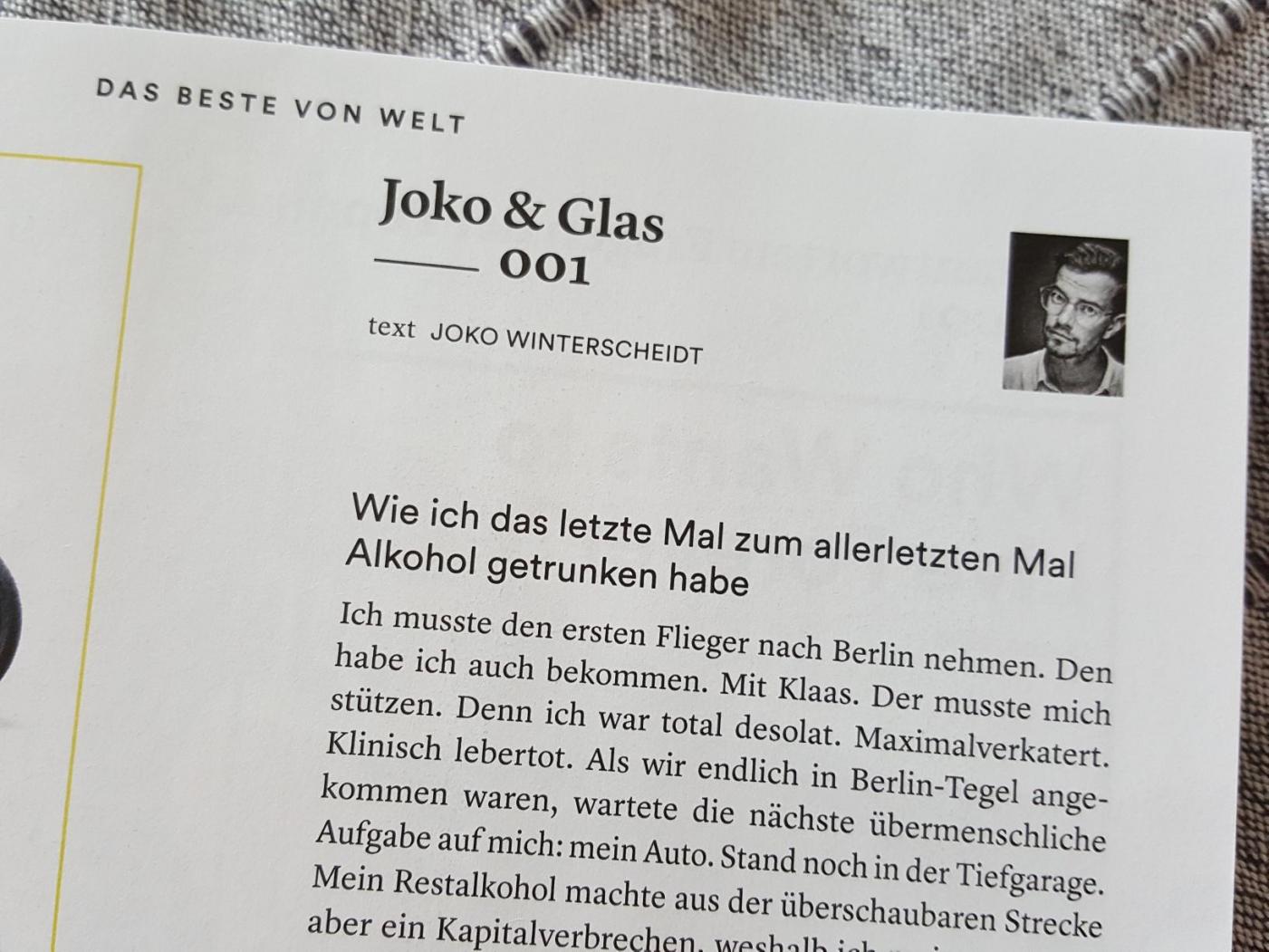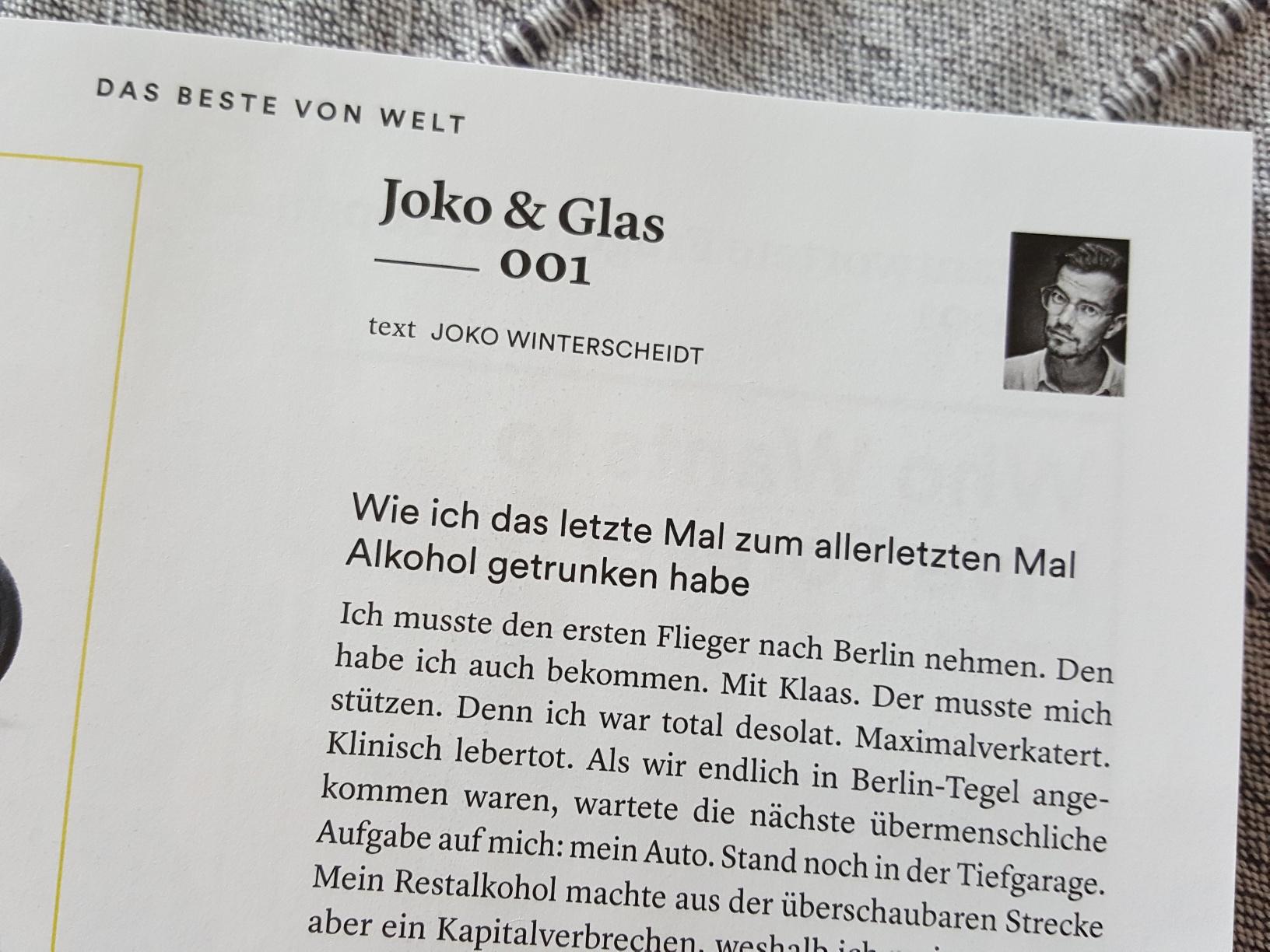
Schriften von JWD-Magazin
suche die im neuen Magazin von Joko Winterscheid genutzten Schriften für Text ("Brotschrift") und Überschriften. Habe bis jetzt nur gefunden, dass das Layout Heico Forster verantwortet. Würde mich freuen, wenn mir jemand helfen könnte :-)
Gelöst von D2C
Die Überschriften (Sans-Serif) sind in der LL Circular von Laurenz Brunner gesetzt, erschienen bei Lineto.
Fließtext habe ich bereits selbst herausgefunden: die Lyon von Kai Bernau, erschienen bei Commercial Type.
Ja, finde ich auch. Habe für ein Projekt damals die Guardian gekauft, aber werde auf die Lyon ganz sicher auch ein Auge werfen. Die Circular hat einen stolzen Preis, da muss ich noch überlegen :-))
Vielen Dank für den Hinweis, Superseite! Die Real hab ich sogar schon, dass die der 1. Vorschlag ist, hätte ich jetzt nicht gedacht.. Die Neuzeit Grotesk hatte ich zunächst in Verdacht, die Schrift zu sein, sie läuft nur etwas schmaler, aber die Ziffern 0-9 sind denen der Circular sehr ähnlich. Checke die anderen aber auch mal durch . Die Seite https://www.typewolf.com/site-of-the-day/fonts/lyon-text gibt noch andere Non-Serifen als Kombi an, aber die, die mir gefallen, sind noch teurer als die Circular :-)
Wenn es um Alternativen geht: die Neurial ist vielleicht eine Überlegung wert (Deni Anggara für Indian Type Foundry, 2018). Sie hat zumindest auch das im Moment so angesagte /t mit dem Radius in der Stamm-Querstrich-Ecke (war die Circular eigentlich die erste Schrift mit diesem Merkmal?). Die Schriften von Indian Type Foundry sind außerdem in der Regel recht gut gehintet, falls das für dich eine Rolle spielt. Die Circular dagegen bröckelte stellenweise auf weniger hochauflösenden Displays, als ich mal mit ihr fürs Web gearbeitet habe. Dafür hat die Neurial keine »echte« Kursive, nur Oblique-Schnitte.
Dann gibt es noch die Neuzeit Office als Alternative (Akira Kobayashi für Linotype, 2006) – ähnlich der auch von Identifont vorgeschlagenen Neuzeit S, aber etwas luftiger als diese. Sie hat mal in einem Projekt von mir die Circular ausgestochen. Ohne Sonderangebot ist die Neuzeit Office aber zugegebenerweise ebenfalls mager ausgestattet für’s Geld.
Wow, Danke für die sehr guten Tipps! Bei der Indian Type Foundry habe ich ein Auge auf die Tara geworfen (gerade im Angebot), war mir aber nicht sicher, ob die auch wirklich gut gehintet ist, bin da schon öfter reingefallen. Insofern war Ihr Tipp entscheidend, vielleicht doch die Schrift zu erwerben ;-)
Zurück zur Curricular: Die Neurial passt m.E. am besten zur Lyon (z.B. kleines "a"), die Neuzeit Office sieht der Circular am ähnlichsten (bis auf einige Feinheiten, z.B. das große "J"). Preislich sind das sehr gute Alternativen!
Finde ja auch, dass zur anderen großen Schrift von Commercial Type, der Guardian, die Grotesken gut passen. So hatte ich in einem früheren Projekt die Guardian mit der Real (im Medium-Schnitt) kombiniert. Jetzt habe ich der Guardian in einem neuen Projekt die Guardian Sans Narrow zur Seite gestellt und wenn ich mir so das JWD-Heft ansehe, finde ich, dass die Grotesken - auch im Regular-Schnitt - besser passen, irgendwie ruhiger aussehen. Die Real ähnelt ja ein wenig der Neurial und wird von Identifont als ähnlichster Font zur Circular angesehen ... Muss noch mal puzzeln und ggf. umstellen ... schade ums Geld für die Guardian Sans, aber vielleicht ergibt sich da nochmal was ... ;-) Besten Dank erstmal, Ihr habt mir alle sehr geholfen!
Die hat aber leider kein Versal-Eszett!
Ah, guter Hinweis, vielen Dank! Bin auch von der Tara wieder abgerückt, hatte mir den Testfont heruntergeladen und war nicht begeistert. Als Non-Serife zur Guardian habe ich jetzt die Univers genommen, musste nach dem (vergeblichen) Kauf der Guardian Sans ein wenig aufs Budget achten ;-)